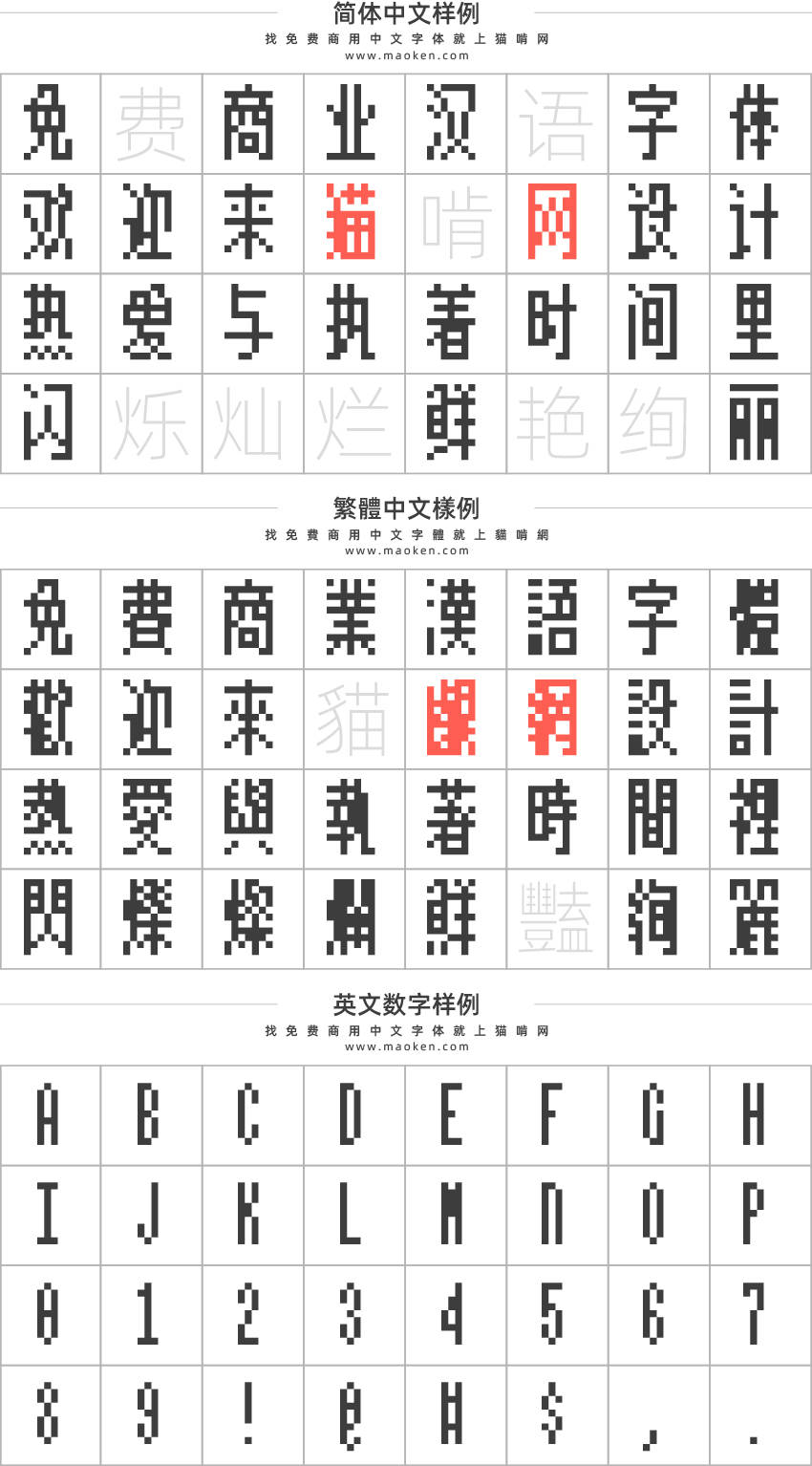
目哉像素体:Diaowinner出品 k8x12像素字体补简计划 免费商用
字体作者:diaowinner (中国大陆) 字体字重:1个
目哉像素(曾用名 k8x12j)是一个基于 k8x12 的 8×12 中日文点阵(像素)字体。亿一些字形、部件参考了最像素。对此表示感谢。
• 目哉像素更新至 2.0.20241013 版,跟进了 ItMarki k8x12+ 的修改,覆盖了 GB/T 2312、现代汉语通用字表、通用规范汉字表、汉仪简繁字表、IICore、台常用「国字」标准字体表、五大码常用汉字表、常用字字形表、GB/T 12345 等字表。目哉像素第一阶段结束。
• 目哉像素体第一版正式发布